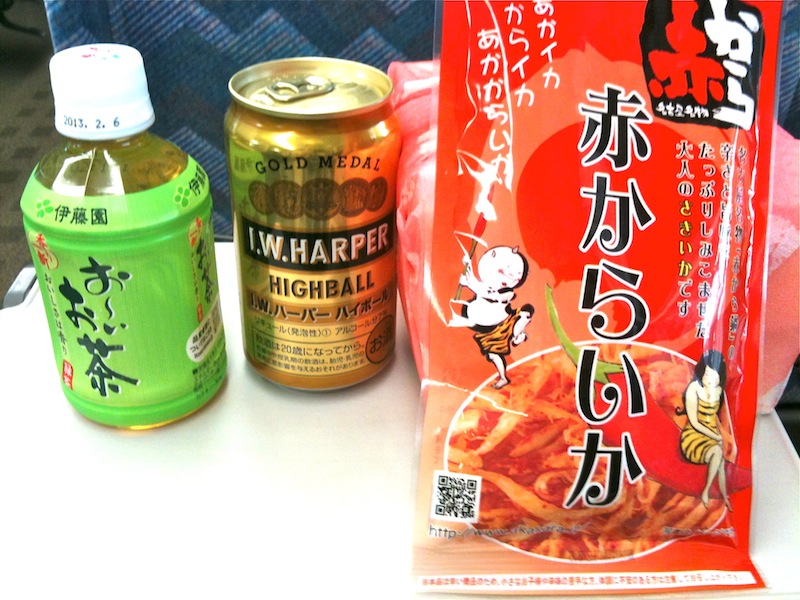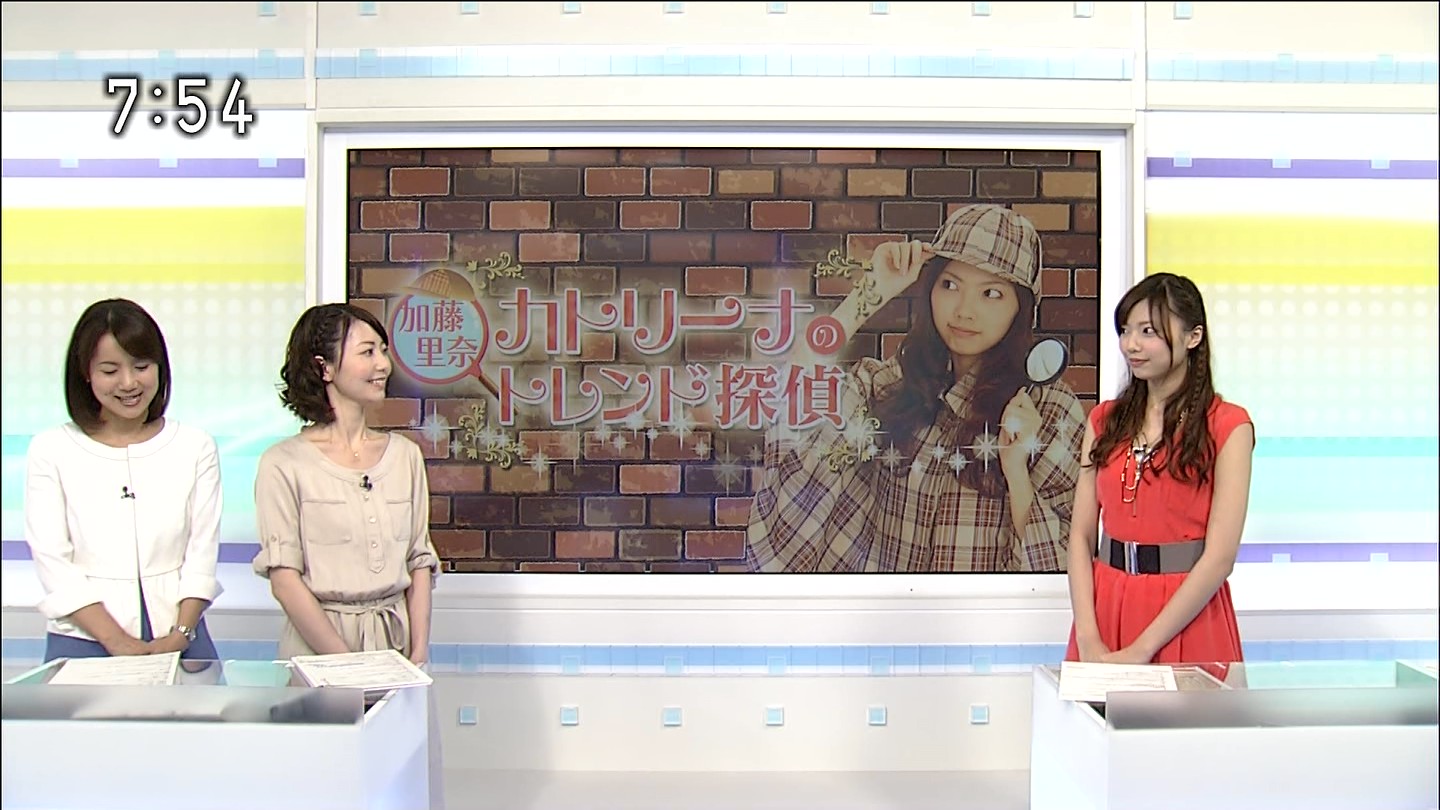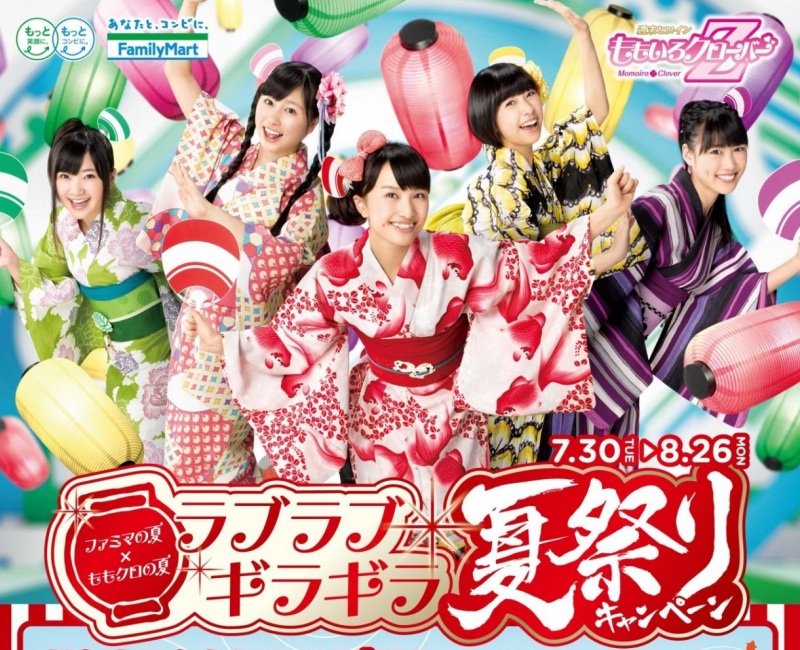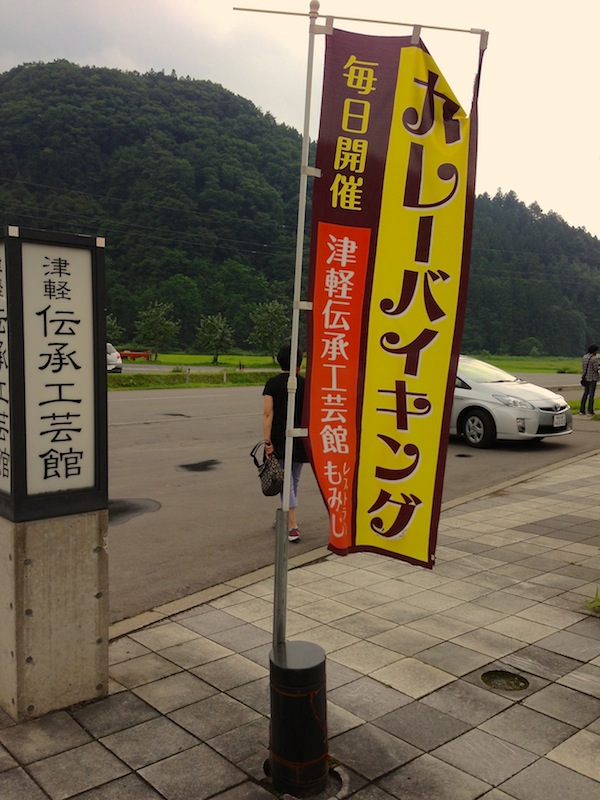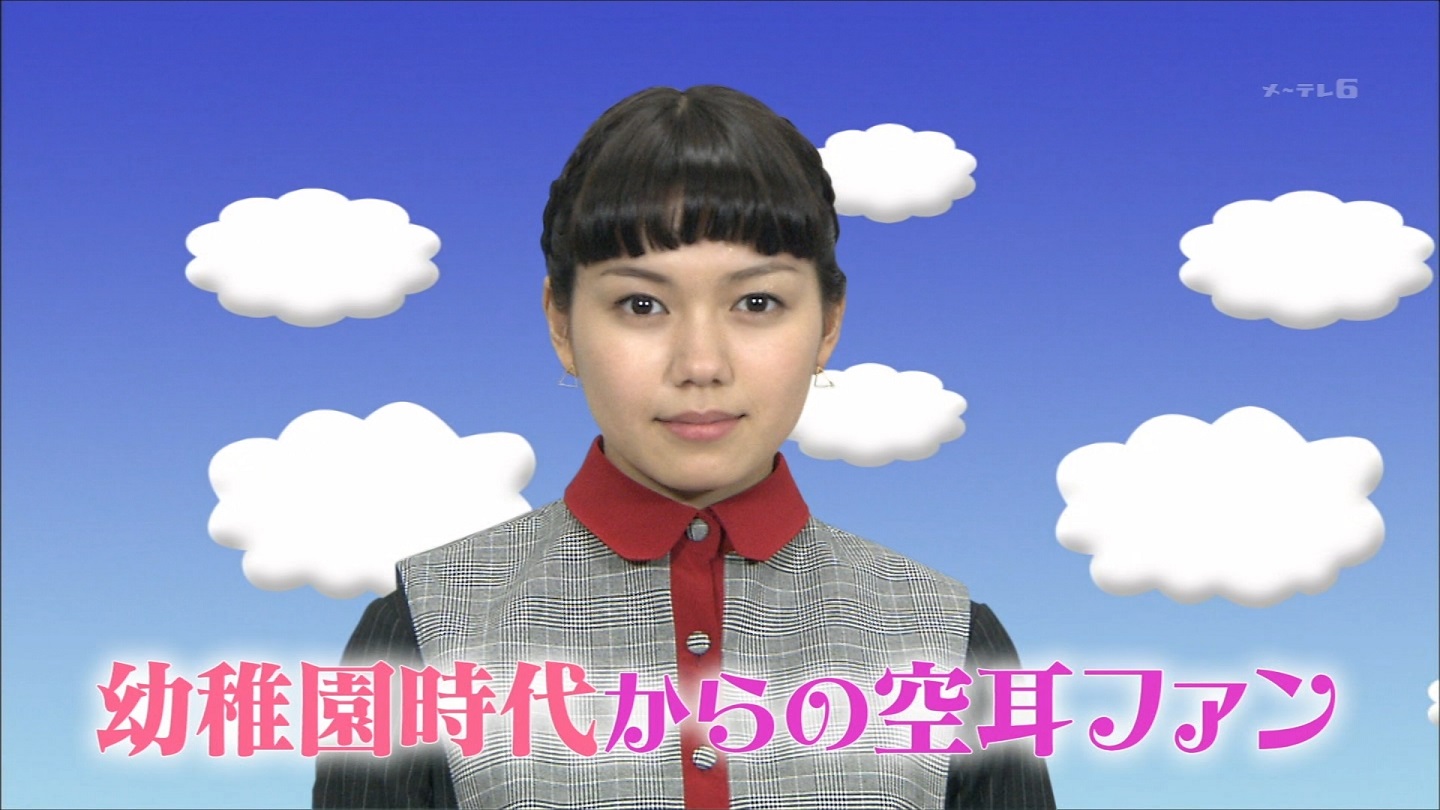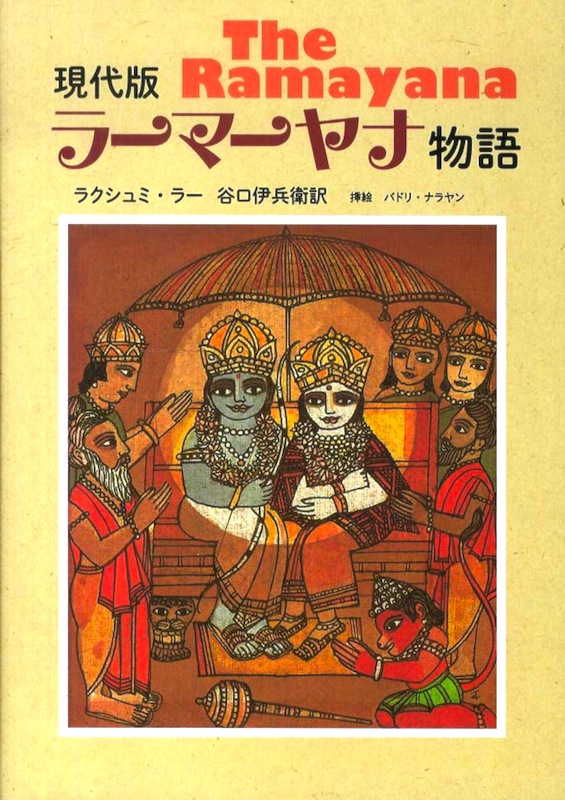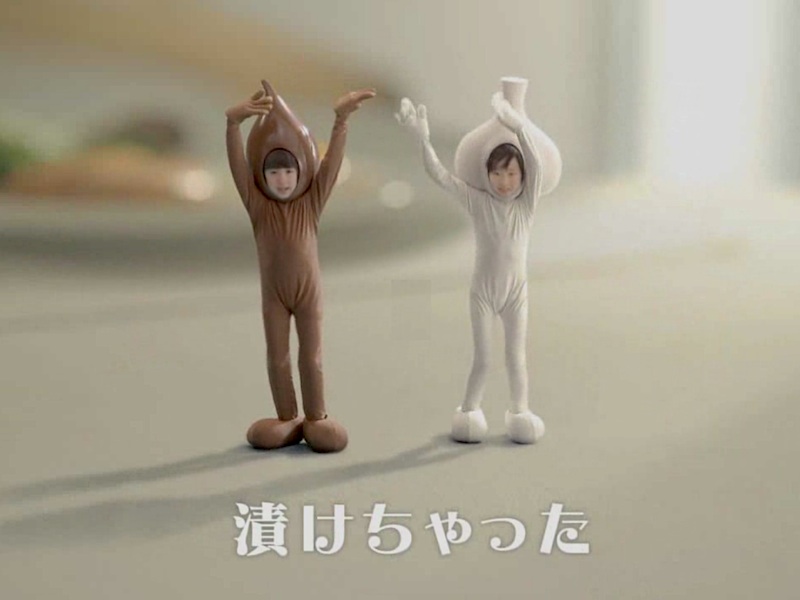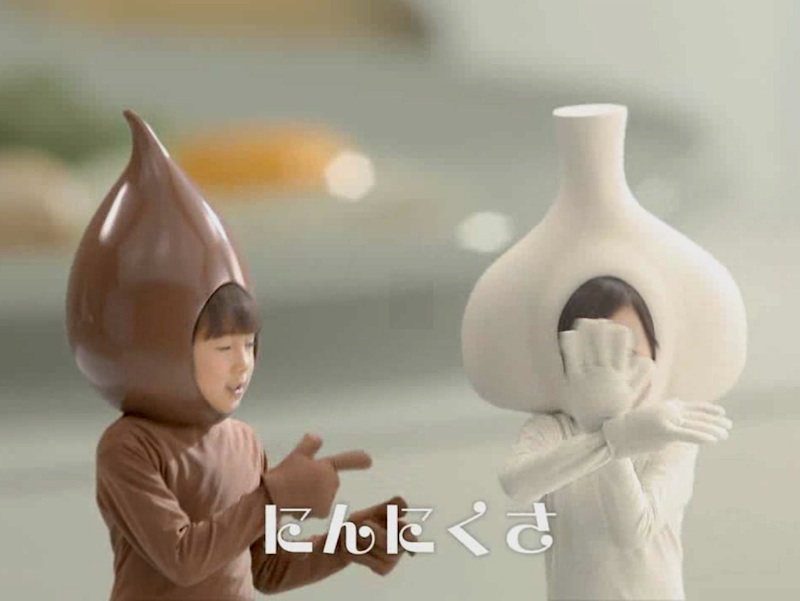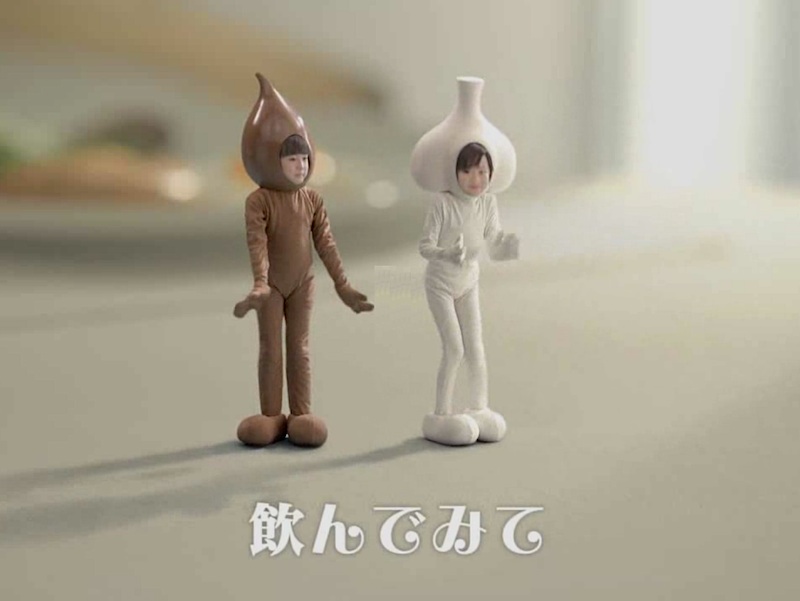
地域情報誌の記事タイトル さとうゆたか
新聞と一緒に折り込まれてきた情報誌。
コンビニのキャンペーンロゴ さとうゆたか
キャンペーンの内容はこちら↓。
連載小説の扉ページ さとうゆたか
「か」の右の点、「ぶ」の左右の点、角度と位置が微妙に変更されている。
脱毛サロンの広告 さとうゆたか
きのう地下鉄の車内広告で見かけた。
絵本 さとうゆたか
とてもキレイに角を丸く処理してある…。
キャンペーンロゴ さとうゆたか
北千住ルミネで催されているスタンプラリー。
オモチャのパッケージ さとうゆたか
もう1点 さとうゆたか
本の表紙 さとうゆたか
横用の音引きを、無理にタテにしている…。
本の表紙 さとうゆたか